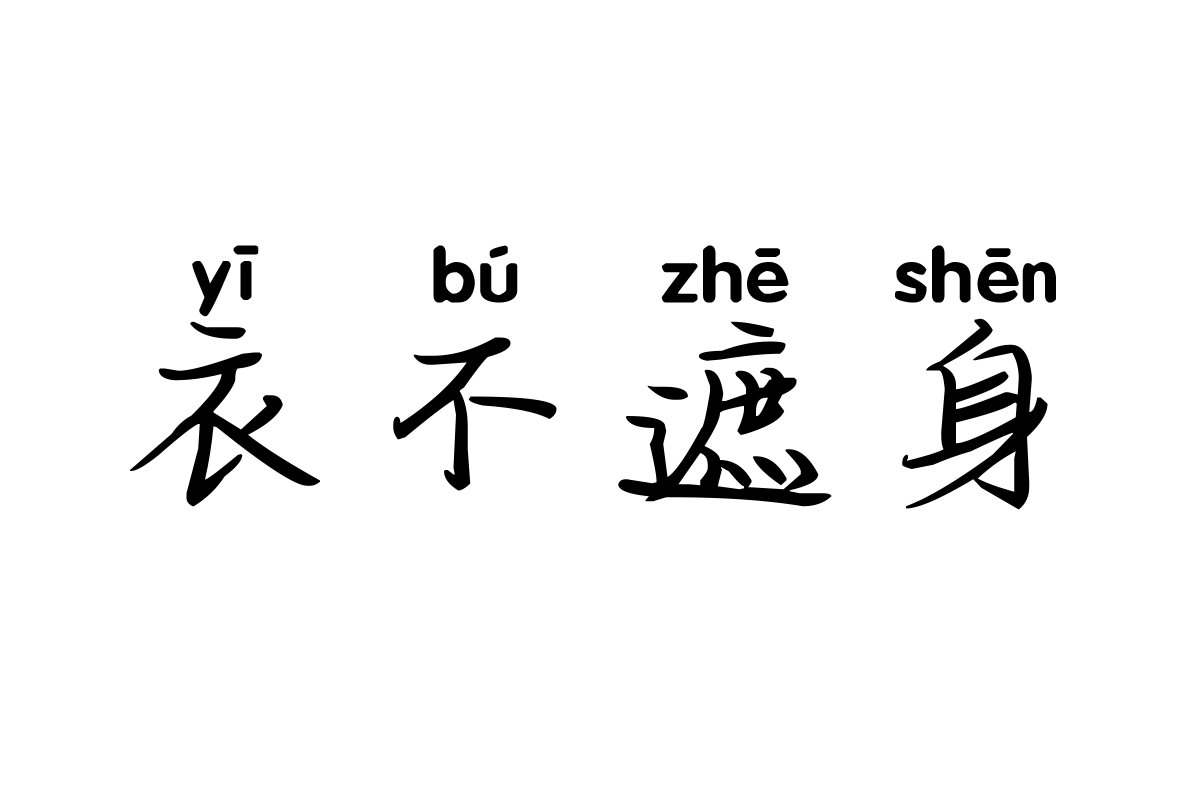
米开花季情书拼音体是一种中文字体,由设计师设计并命名为“米开花季情书”。这种字体的特点是将汉字的笔画和结构进行了重新组合,使其更加美观、易读。
1. 字体特点:米开花季情书拼音体的特点是笔画流畅,结构紧凑,整体呈现出一种简洁、明快的风格。它适合用于各种需要突出文字美感的场合,如书籍、杂志、海报等。
2. 字体风格:该字体的风格独特,既有现代感,又不失传统韵味。它的线条流畅,给人一种轻松愉悦的感觉,仿佛在欣赏一幅美丽的画卷。同时,由于采用了拼音元素,使得这种字体更具亲和力,能够引起读者的兴趣。
3. 字体适用范围:米开花季情书拼音体适用于各种需要突出文字美感的场合,如广告、宣传册、网页等。它能够很好地与各种背景色搭配,使文字更加醒目,提高阅读体验。
4. 字体优缺点:米开花季情书拼音体的优点在于其独特的风格和优美的视觉效果。然而,由于其笔画复杂,对于不熟悉中文书写的人来说,使用起来可能会有一定的难度。此外,该字体的可读性相对较低,对于需要快速阅读的场景可能不太适用。
总之,米开花季情书拼音体是一种独具特色的中文字体,适合用于需要突出文字美感的场合。然而,对于不熟悉中文书写的人来说,使用起来可能会有一定的难度。